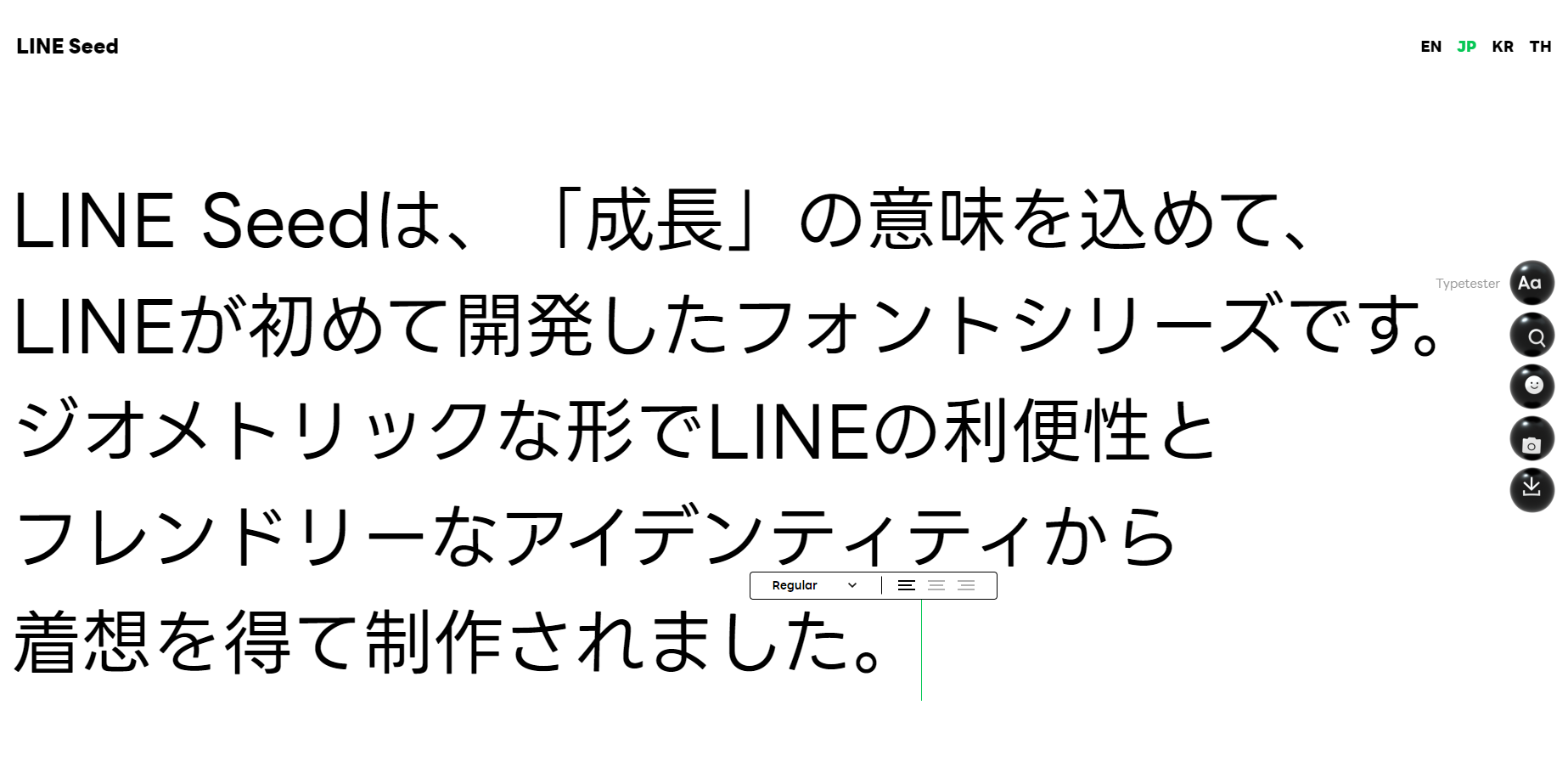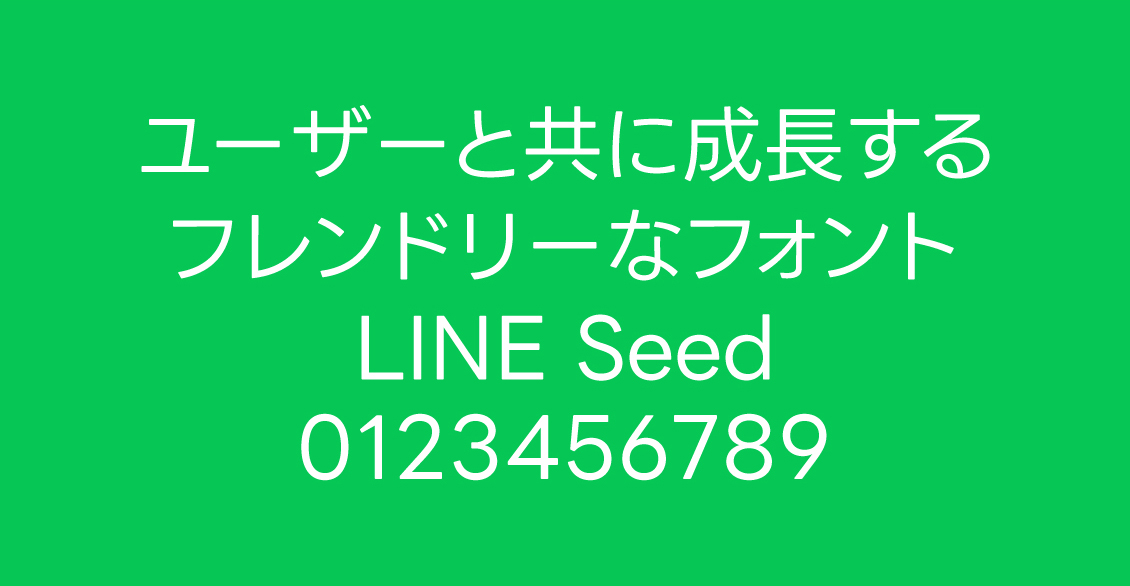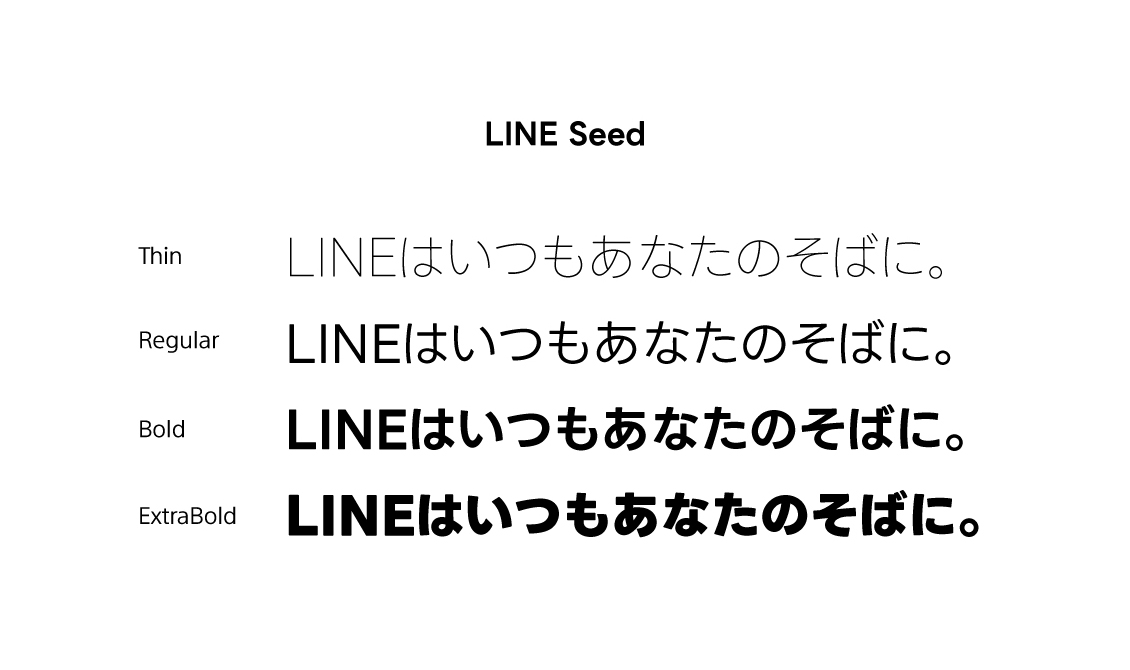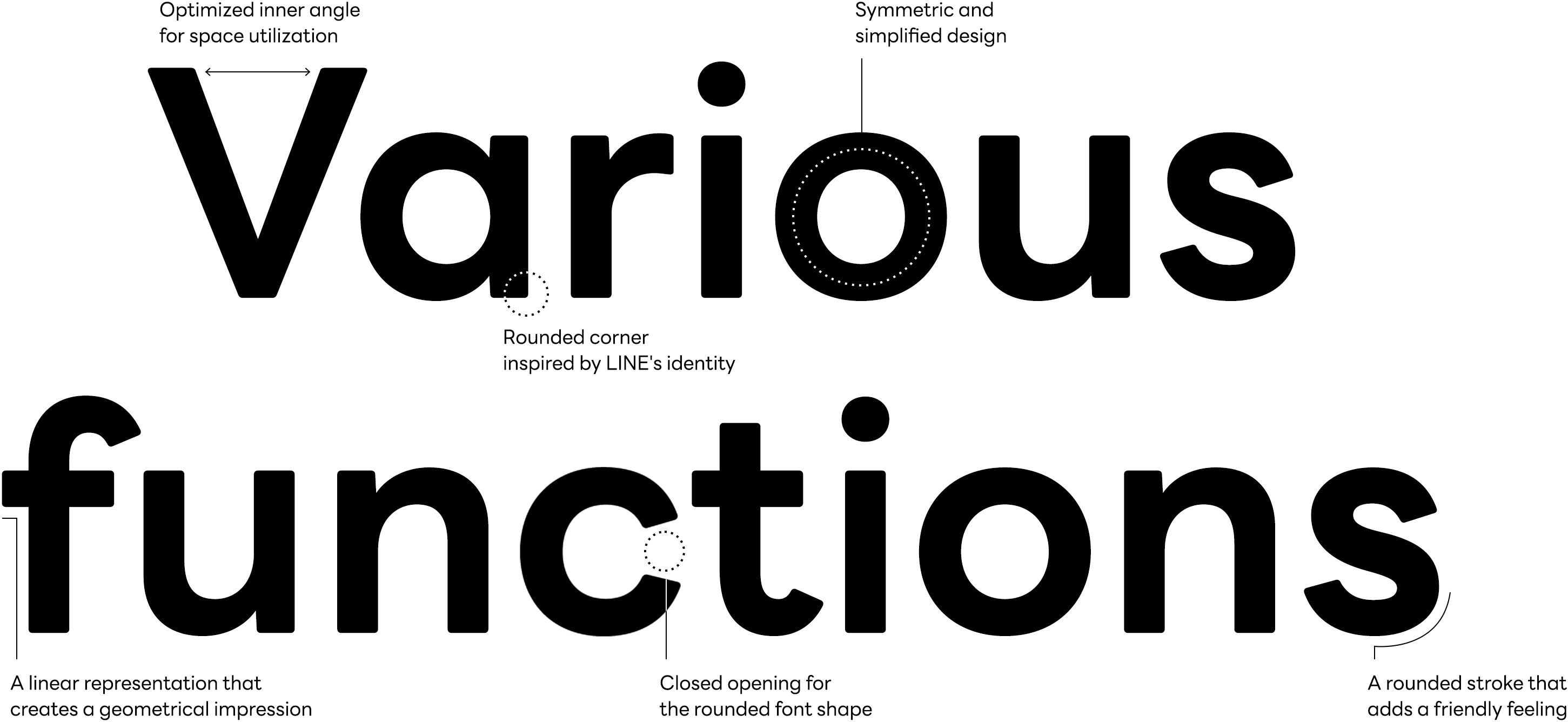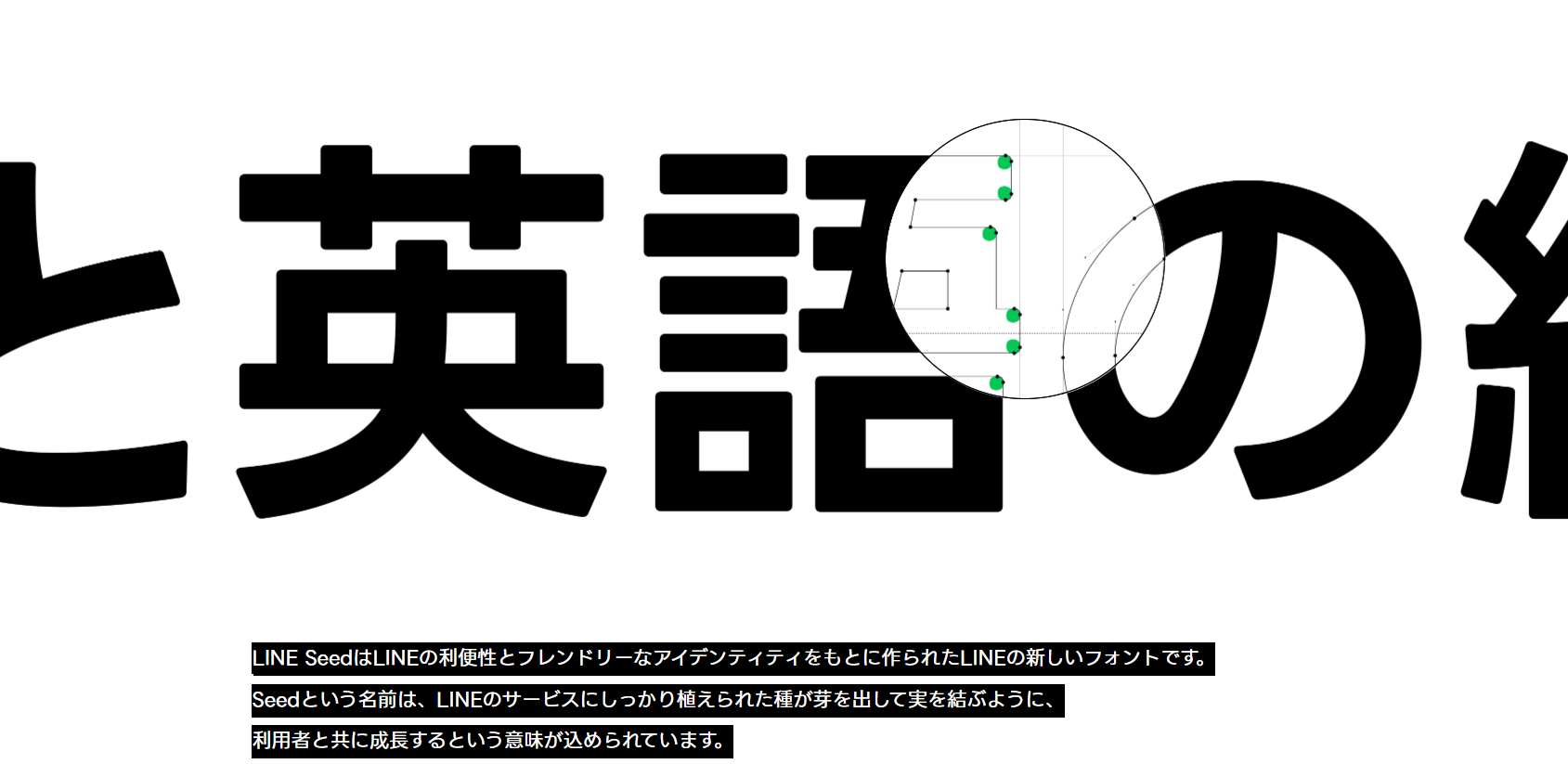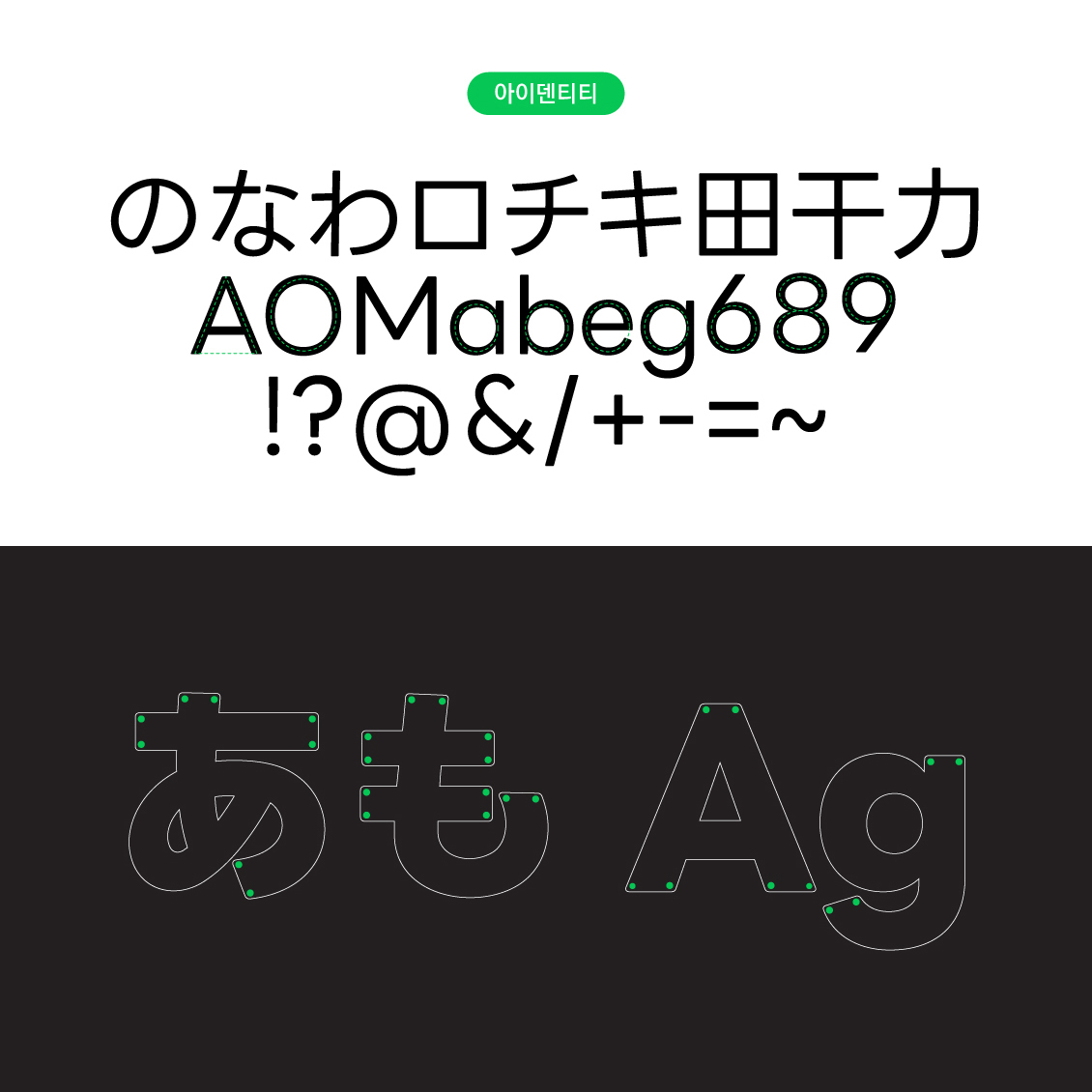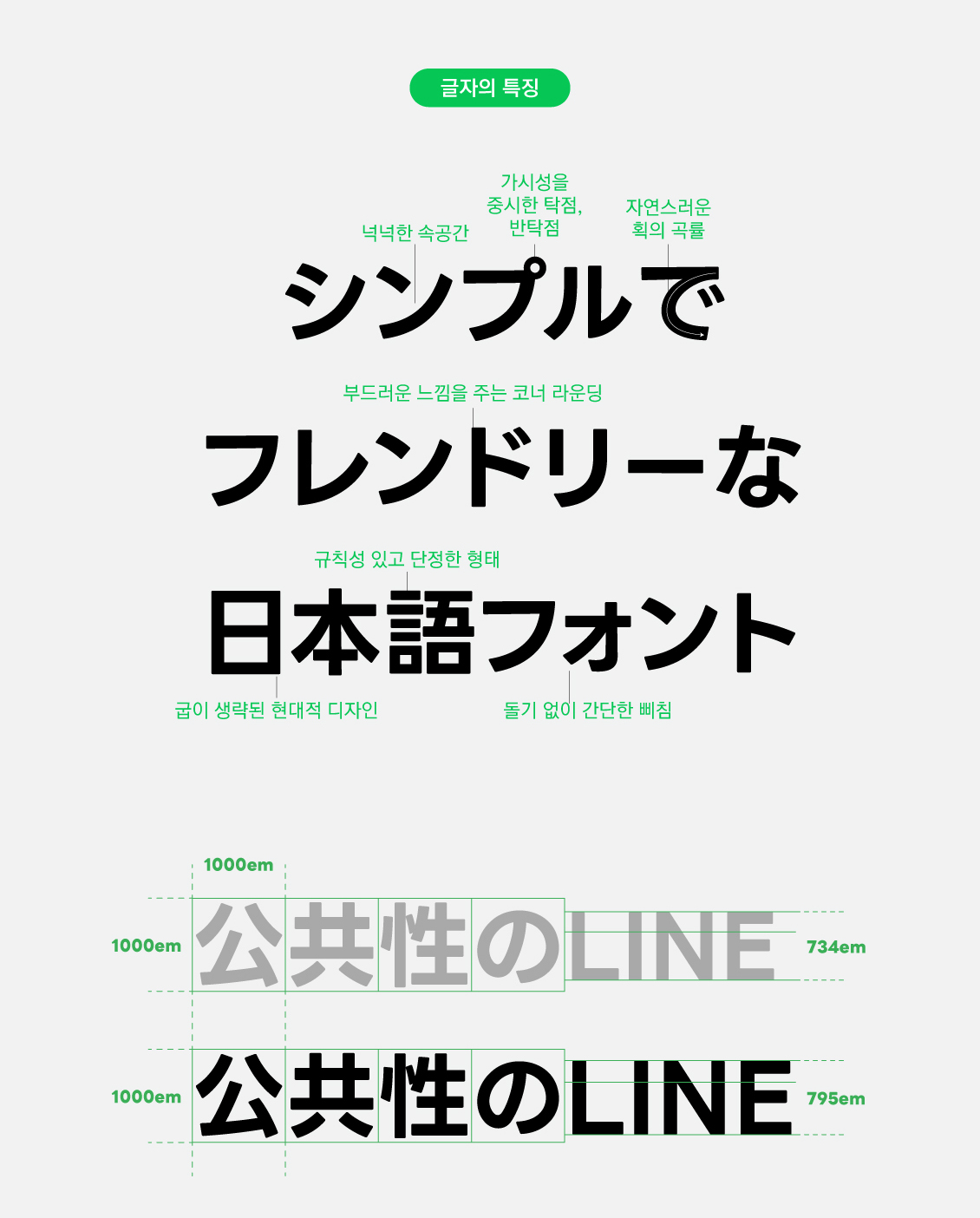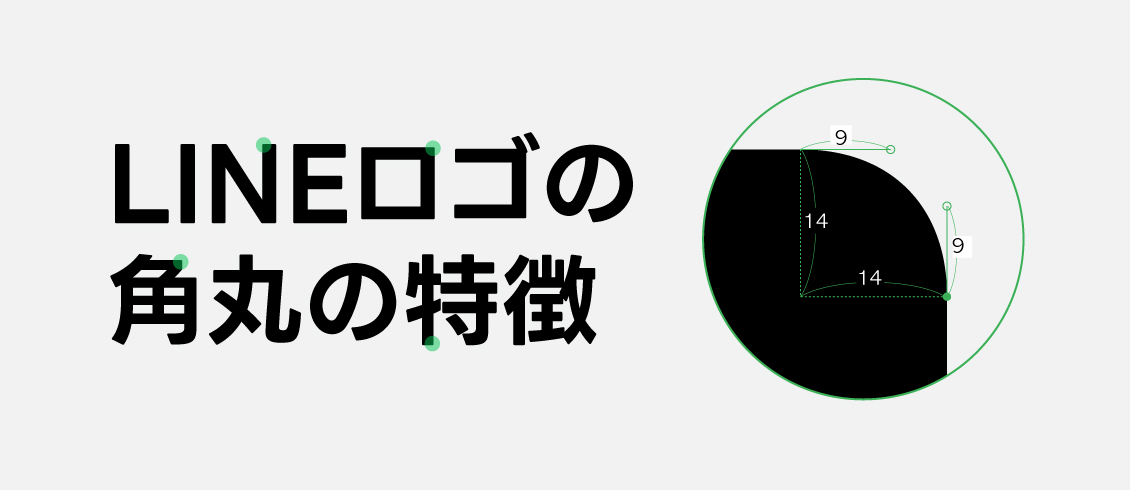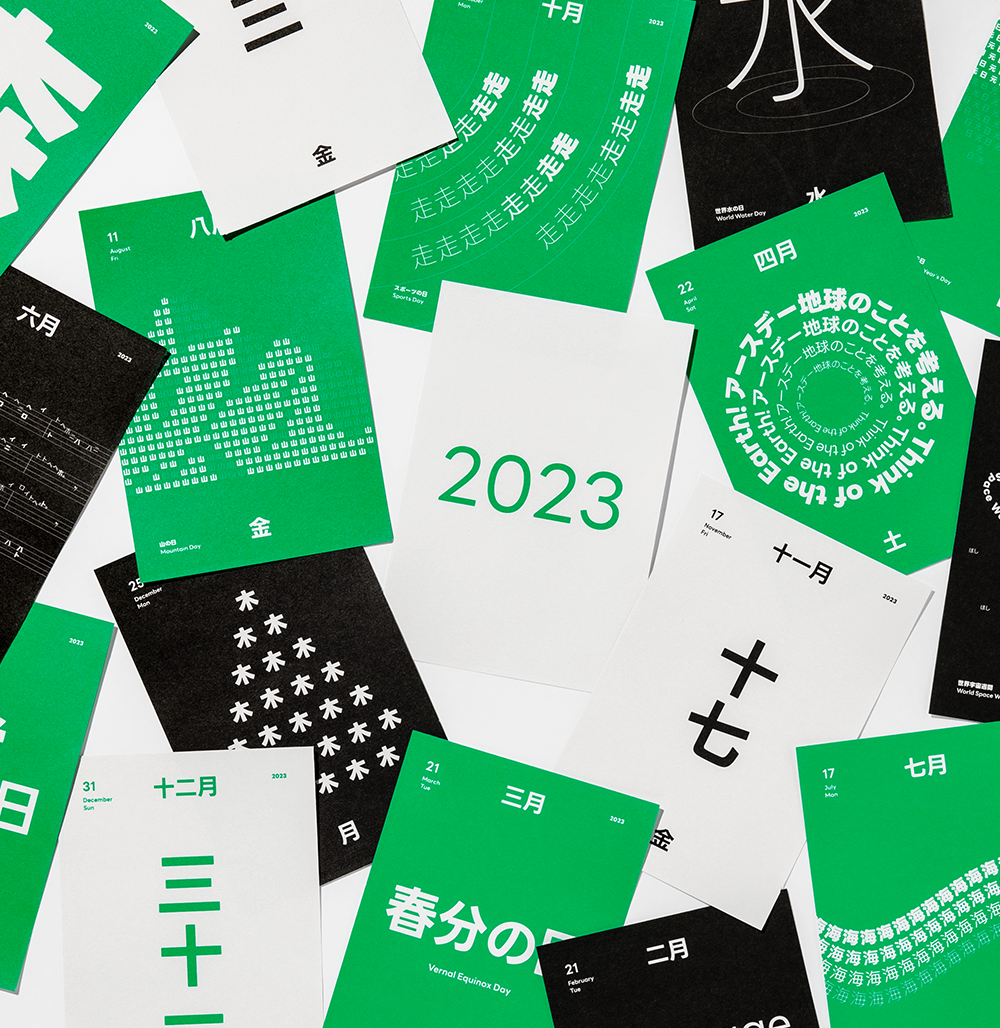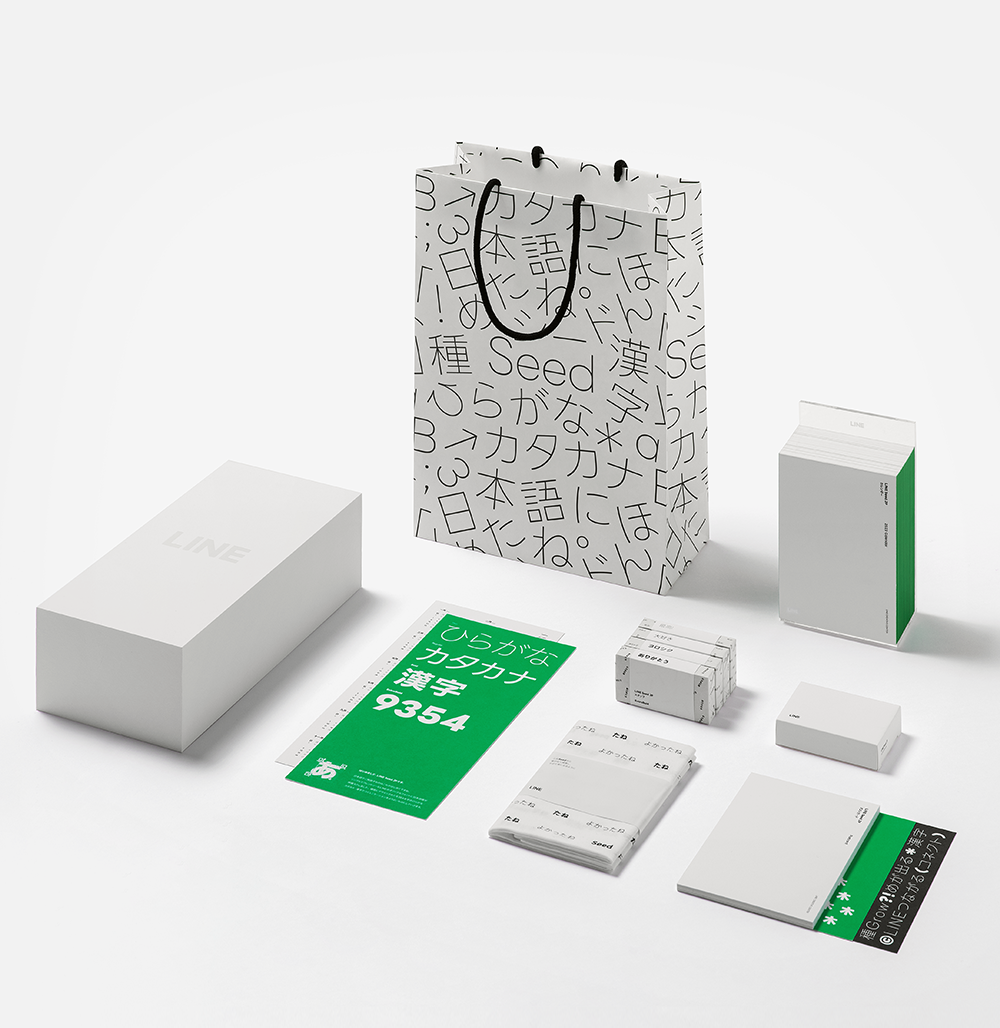
오늘 알아볼 전용서체는 한국의 카카오와 같은 일본의 국민 채팅앱, 글로벌 모바일 메신저 기업 LINE의 전용서체 「LINE Seed」입니다. 폰트릭스는 한글뿐 아니라 영어, 일문 등 세계 다양한 언어로 된 전용서체 제작도 하고 있는데요. 이번 서체는 LINE Seed 일문 서체로 폰트릭스 X Fontworks X 라인 플러스가 협업하여 2년 여의 기간 동안 공을 들여 제작한 큰 프로젝트입니다.
LINE다운 서체를 만들다
LINE Seed는 단순함에 중점을 두고 LINE다운 부드러움을 살린 고딕 서체로, 다른 언어와의 균형과 편리성을 고려한 디자인과 총 네 가지 굵기로 파생되었습니다. LINE 로고의 기하학적 형태를 유지하면서도 부드러운 곡선으로 가독성, 판독성을 높였습니다.
먼저 개발된 LINE Seed 영문 아이덴티티를 히라가나, 가타카나와 한자에 넣으면서 가독성과 편리성을 유지하는 것이 이번 프로젝트의 목표였습니다. 영문의 디자인 디테일을 유지하며 일문의 볼륨과 무게 중심의 균형을 맞추어 서로 어울리게 작업했습니다.
LINE Seed의 정체성과 특징
LINE Seed의 심플한 형태는 LINE의 보편성과 친절함을 나타내며, 둥근 모서리는 문자, 숫자, 기호, 아이콘을 포함한 모든 텍스트에 공통된 아이덴티티로 적용됩니다.
글로벌 사용자에게 일관된 메시지를 전달하기 위해 다양한 언어로 제작되어, 언어별로 문자의 고유한 형태와 기능을 유지하면서 통일성 있고 자연스럽게 읽힐 수 있도록 고려하여 디자인했습니다.
서체의 형태는 자연스럽고 부드러운 영문 LINE Seed 서체와 일본어 문자의 크기가 조화를 이루되, 다른 일문 서체에 비해 사이즈가 작아 보이지 않도록 적절하게 크기를 조절했습니다.
LINE Seed의 모든 언어에 적용되는 공통된 아이덴티티인 워드마크의 둥근 모서리를 일본어 폰트에도 동일하게 적용했습니다.
LINE Seed의 활용
서체 소개 및 다운로드 페이지에서 다양하게 활용된 이미지를 볼 수 있는데요. 4종의 웨이트를 사용할 수 있어 깔끔한 패키지나 편집 디자인에도 어울리면서 LINE의 귀여운 캐릭터나 컨셉에 맞게도 활용하기 좋은 것 같습니다.
기업전용서체 제작의 경험이 많은 폰트릭스는 이번 프로젝트에서 그동안의 노하우를 한자 개발과 연계하여 중간 역할을 하고, 전문적인 인력을 바탕으로 서체 개발에 참여하게 되었습니다. 일문은 글자 수가 9,000여 자에 이르고 한글보다 한자의 개발 기간은 몇 배의 시간과 비용이 소요되기에, 일본에서 기업 전용서체를 만드는 일은 극히 드물다고 합니다. 앞으로도 더욱 다양하고 글로벌한 서체 개발에 도전하는 폰트릭스가 되겠습니다 :)